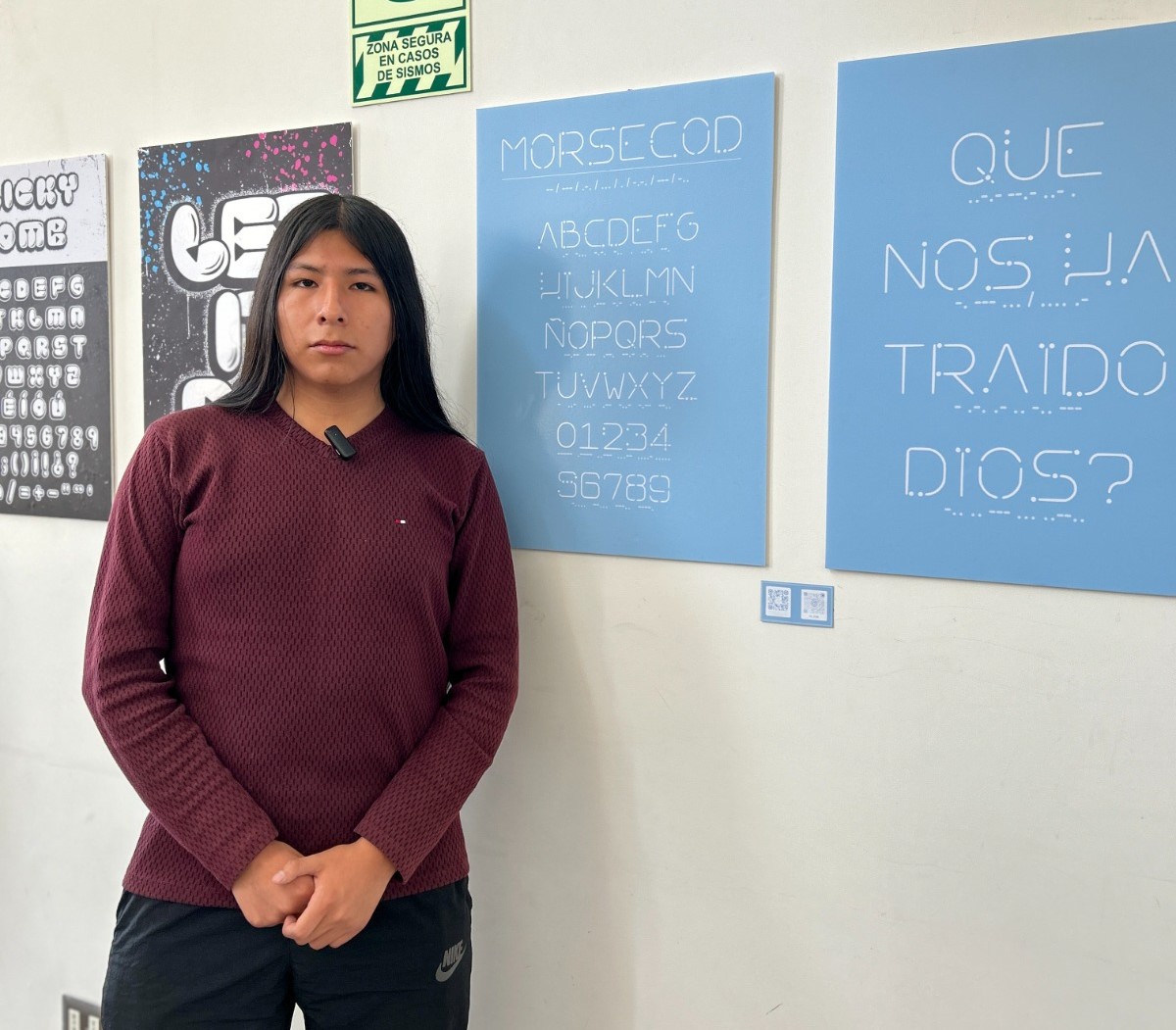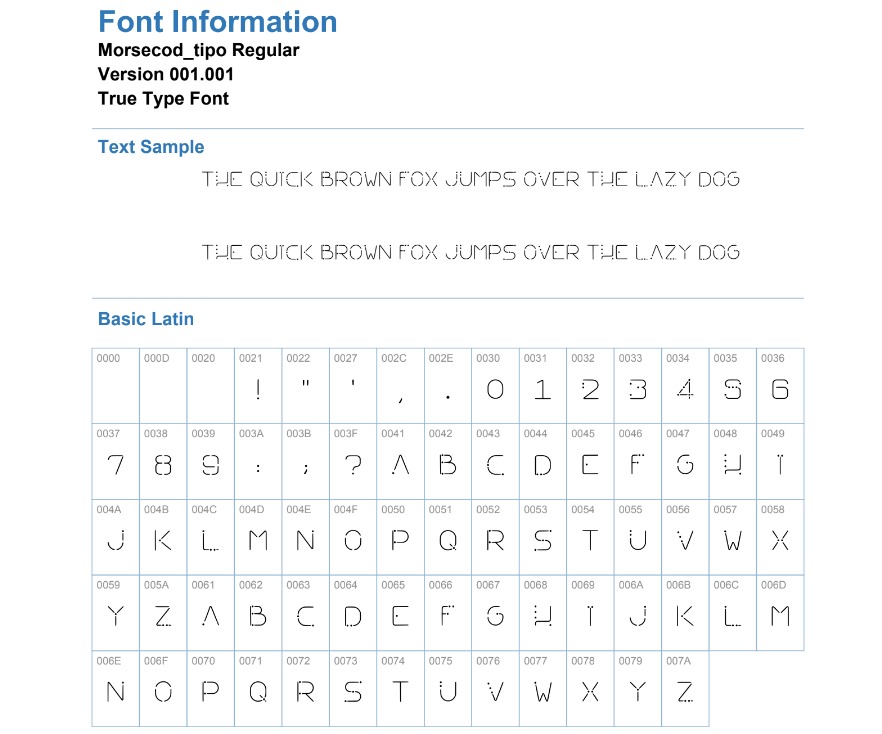
Estudiante peruano crea tipografía basada en el código morse
Morsecod es una tipografía versátil y puede ser utilizada en una variedad de proyectos, desde diseño web hasta impresión.
El joven arequipeño Joe Ccaama, estudiante del primer ciclo de la carrera de Diseño Gráfico en la Escuela Superior Certus de Arequipa, ha creado una tipografía innovadora inspirada en el código morse, el sistema de comunicación que revolucionó la forma en que nos comunicamos a distancia. Esta creación, llamada Morsecod, representa un homenaje a la historia de la tecnología y la importancia de la comunicación en un mundo cada vez más conectado.
El código morse, también conocido como alfabeto morse, es un sistema de comunicación que utiliza puntos y rayas para representar letras, números y símbolos. Fue creado por Alfred Vail en 1837 y rápidamente se convirtió en el estándar para la comunicación telegráfica. El código morse fue fundamental para el desarrollo de las comunicaciones a larga distancia y jugó un papel crucial en eventos históricos como la Guerra Civil estadounidense.
“Siempre me ha fascinado el código morse por ser críptico, agregando su simplicidad y elegancia. Me pareció una idea interesante crear una tipografía que capturará la esencia de este sistema de comunicación y la llevará al mundo del diseño gráfico”, señaló Joe Ccama Pila, el estudiante creativo detrás de esta tipografía sobre su inspiración.
Morsecod se basa en la combinación de puntos y rayas, los elementos básicos del código morse, para crear letras y símbolos únicos. La tipografía es versátil y puede ser utilizada en una variedad de proyectos, desde diseño web hasta impresión.
“La creación de esta innovadora propuesta ha sido bien recibida por la comunidad de diseño gráfico. Muchos profesionales han elogiado la originalidad y la creatividad de la tipografía, así como su potencial para ser utilizada en una variedad de proyectos. Esperamos que esto inspire a otros jóvenes a explorar su creatividad y utilizar la tecnología para crear cosas nuevas e innovadoras” indicó al respecto Yuddy Gallegos, experta en Diseño y Publicidad de la Escuela de Educación Superior Certus. Agregó que “este innovador proyecto ha sido creado gracias a la guía del docente Augusto Carrasco y de toda la plana docente de Certus; en este caso, todos especialistas en tipografía”.
Más allá de la estética
La creación de Morsecod no solo es un logro artístico, sino que también tiene un significado más profundo. El código morse fue una herramienta fundamental para la comunicación durante la mayor parte del siglo XIX y principios del XX. Su uso permitió conectar a personas de todo el mundo, independientemente del idioma que hablaran.
En un mundo cada vez más globalizado y conectado, la tipografía del estudiante del primer año de diseño gráfico nos recuerda la importancia de la comunicación y la capacidad que tiene la tecnología para unirnos.